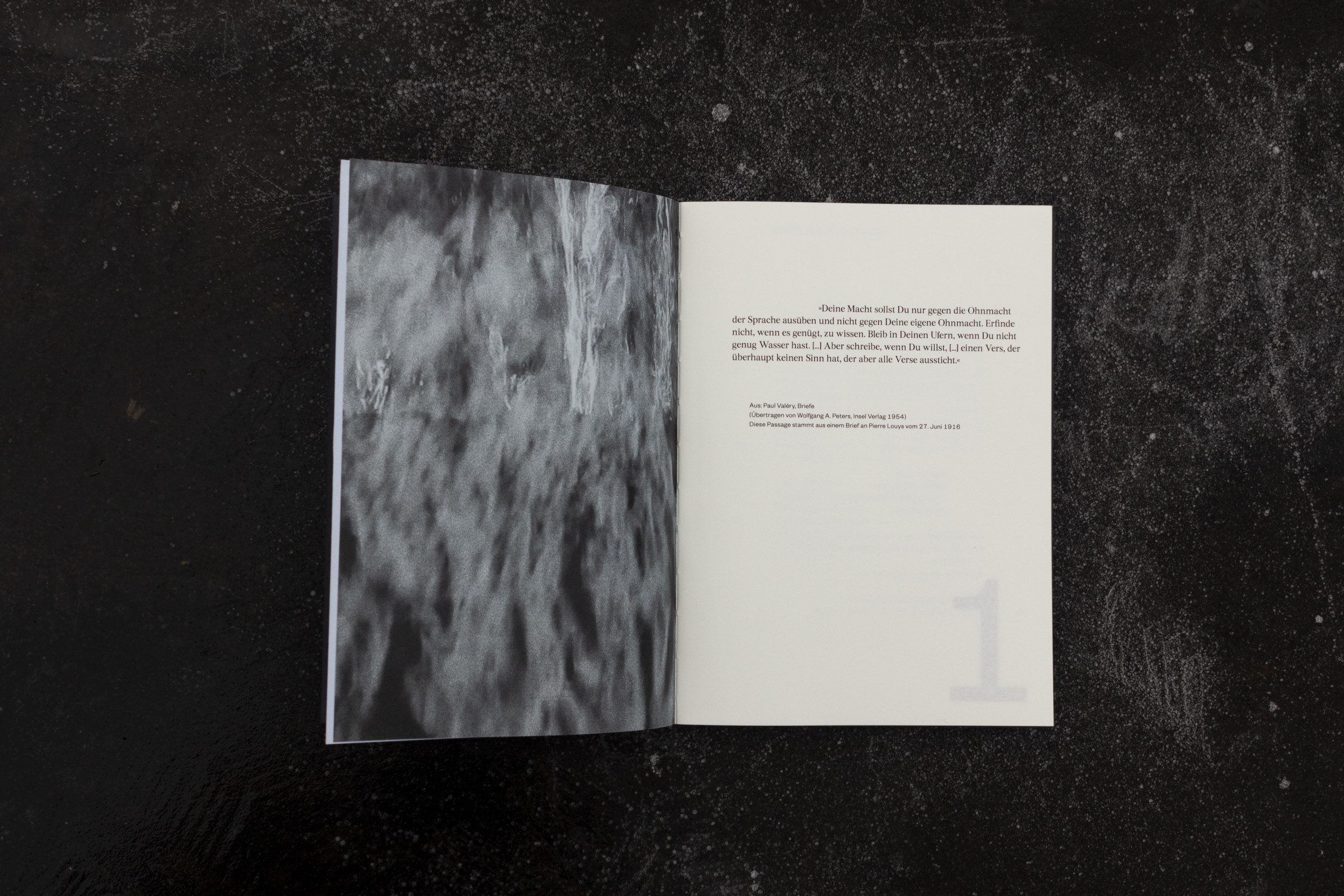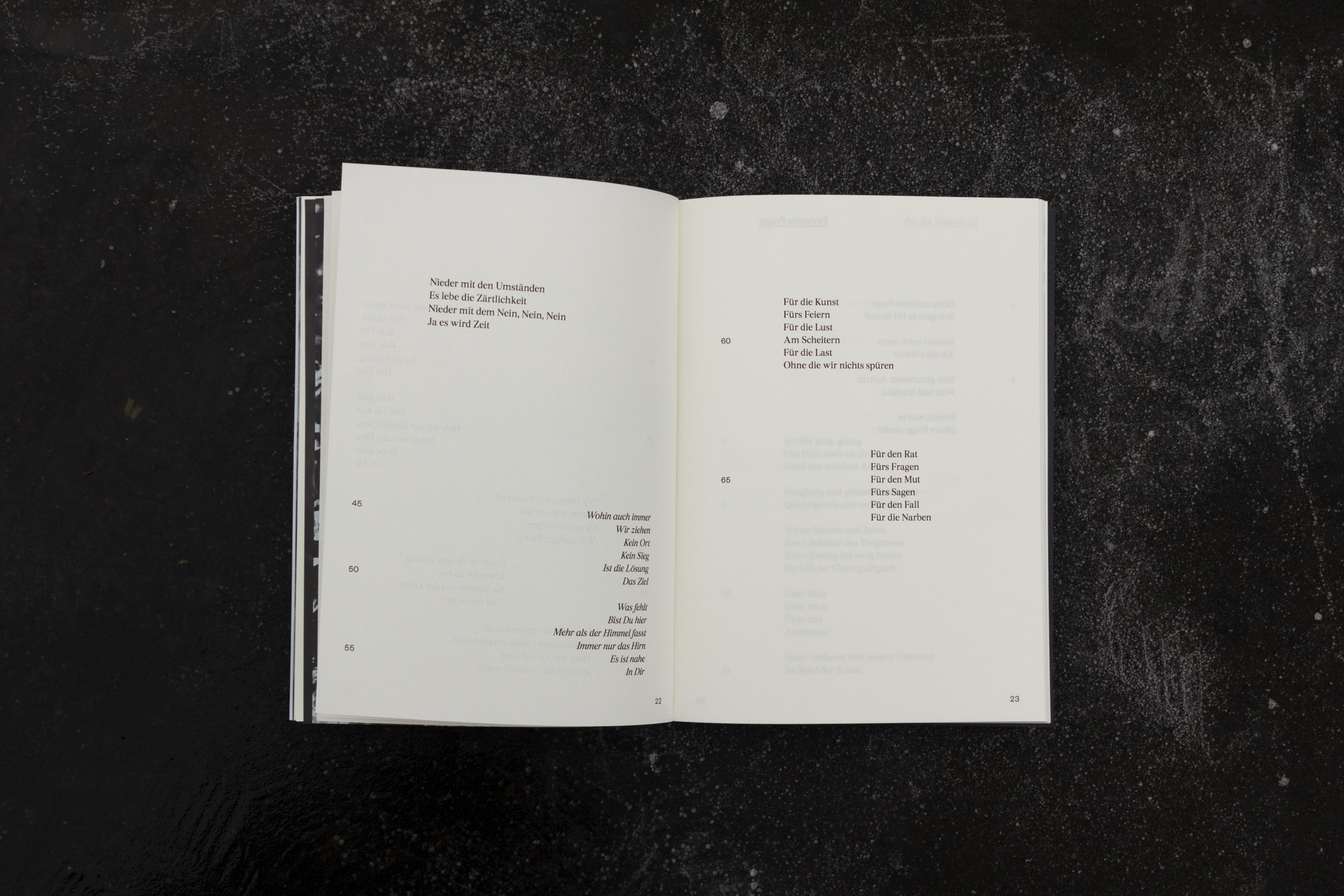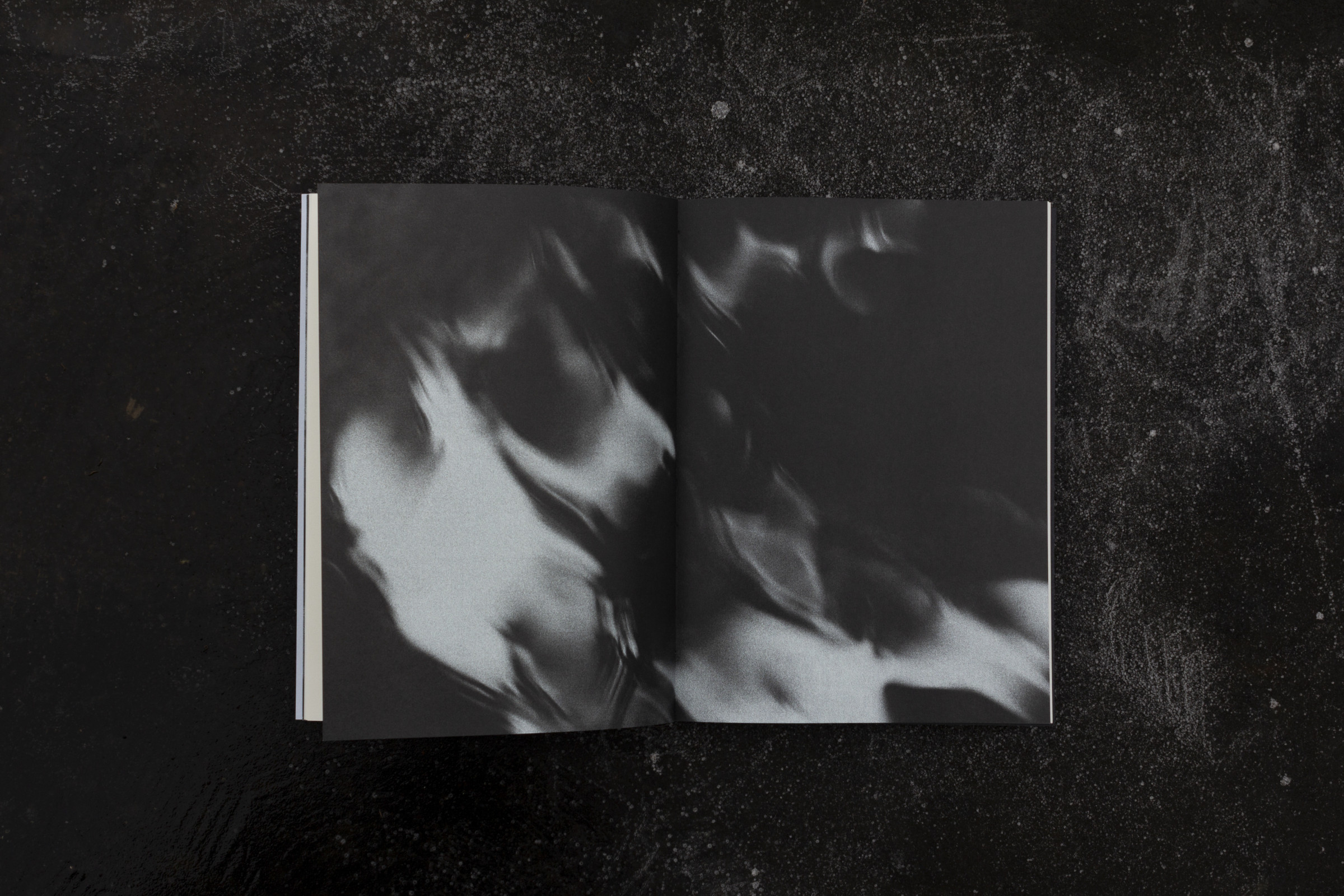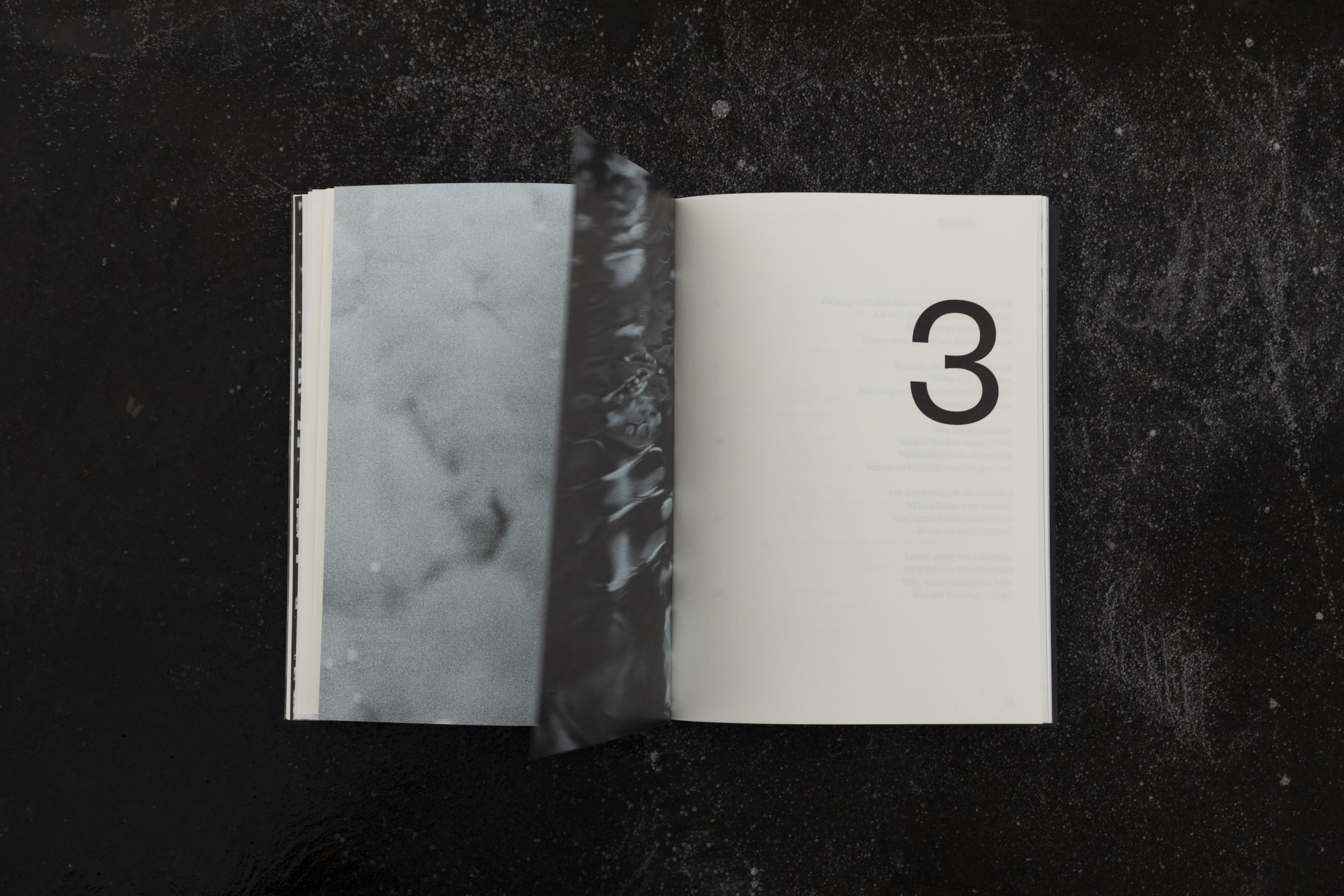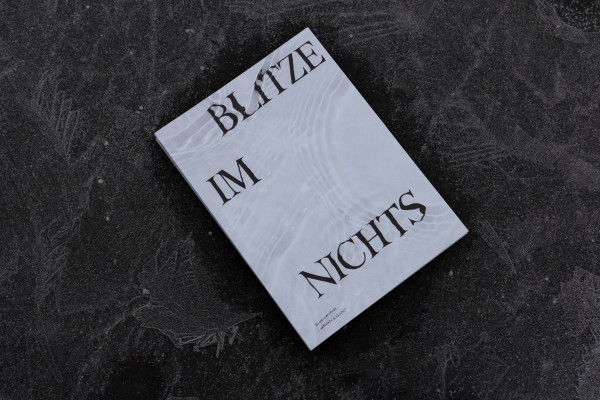
Blitze im Nichts
Buch
Sebastian Król aka Karwendel ist ein Singer-Songwriter aus Hamburg. Blitze im Nichts ist die zweite Publikation mit Songtexten und Gedichten.
Seine Werke sind geprägt von Flüchtigkeit und Abstraktheit, dies spiegelt sich sowohl in der Musik als auch in den Texten wider. In diesem Band verwenden wir abstrahierte Bilder von Wasser, um uns der Thematik zu nähern. Das Cover ist analog entstanden: Dazu wurde die typografische Gestaltung unter Wasser getaucht, sodass die Bewegung des Wassers eine Verzerrung der Buchstaben erzeugt. Die Anordnung der Gedichte und Songtexte folgen der Wellenbewegung und der Melodie der Lieder, so entsteht aauch in der Typographie eine klangliche Welt.
Schrift: Burgess Pro von Colophon Foundry
& Founders Grotesk von Klim Type Foundry